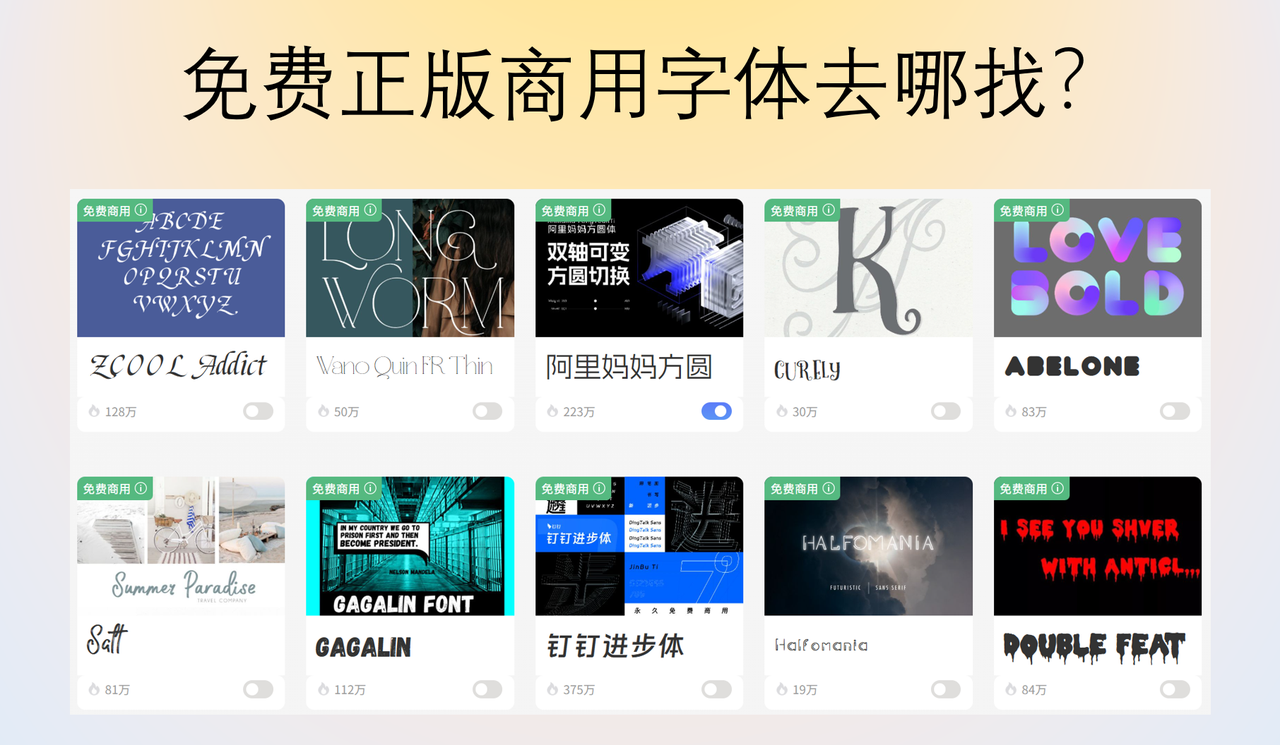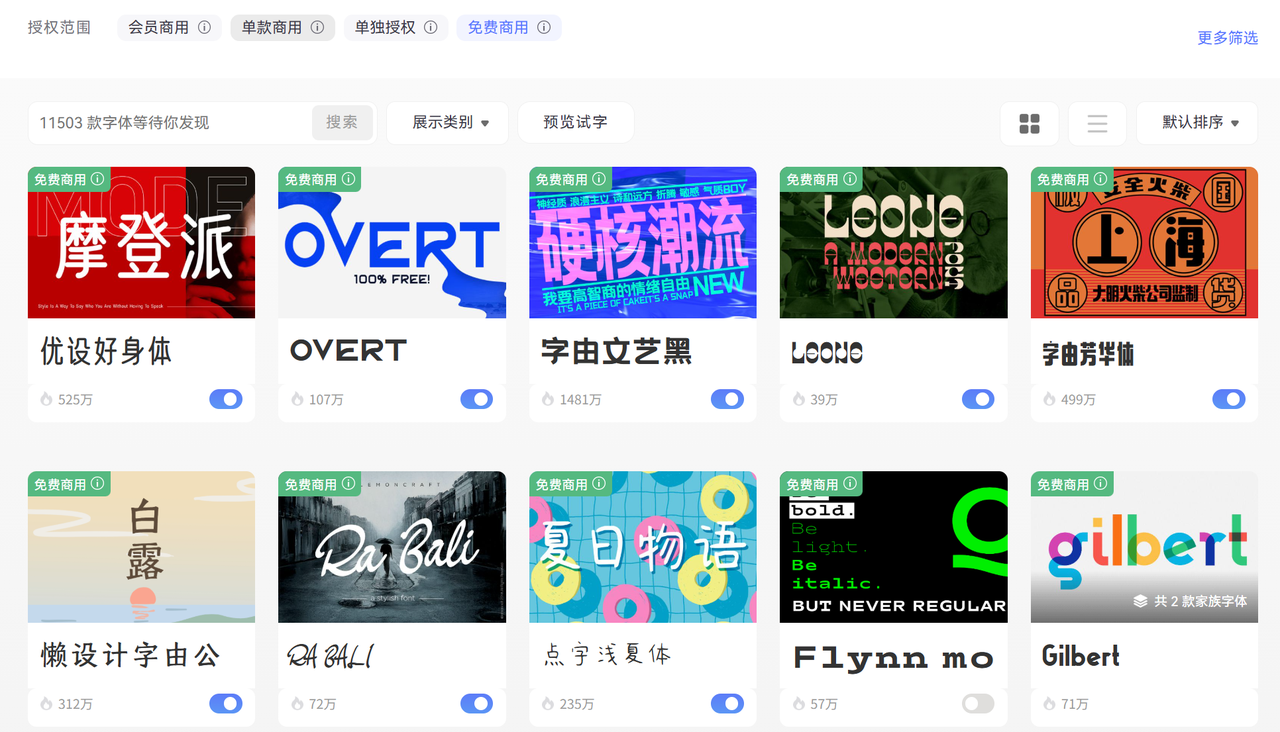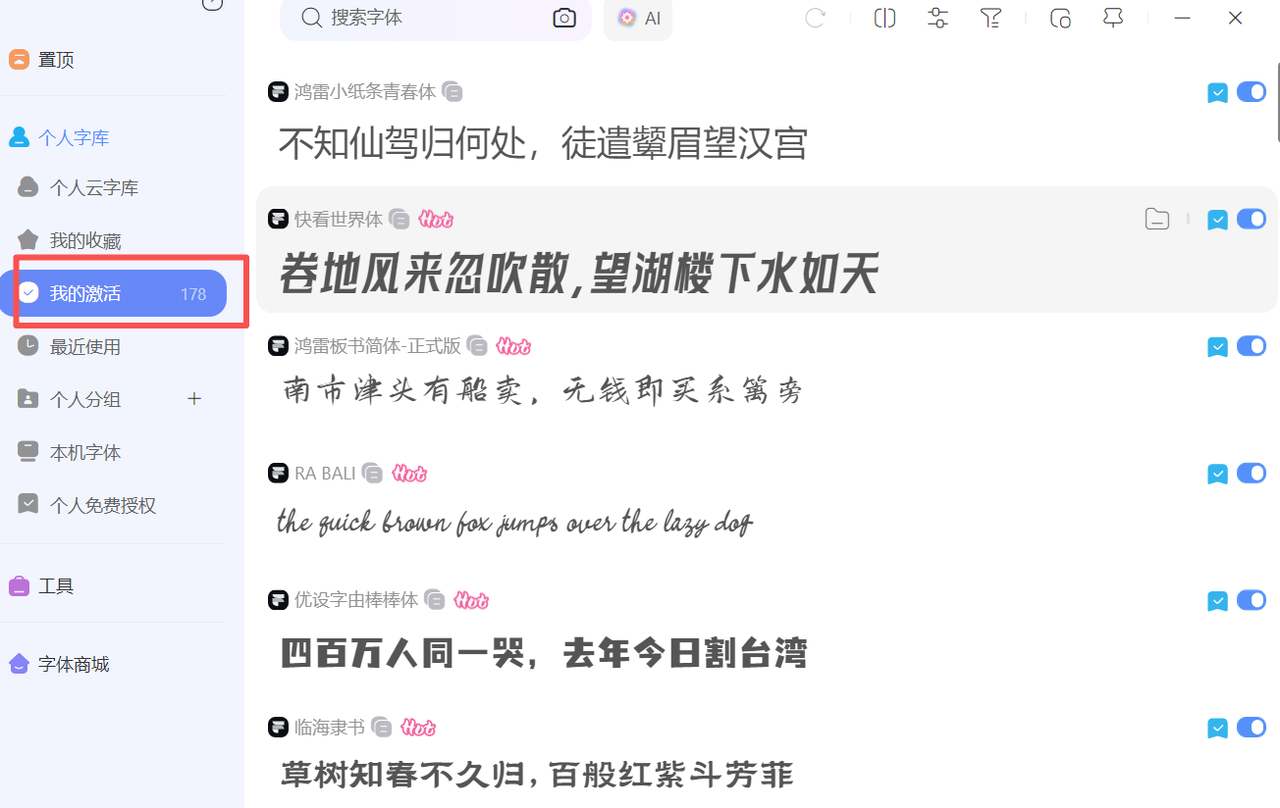
免费正版商用字体去哪找?6个靠谱平台推荐
作为设计师和内容创作者,我深知免费正版商用字体的重要性。每当开始一个新项目,最头疼的问题之一就是:去哪里找可以商用的免费字体?用错字体可能面临法律风险,而付费字体又增加成本。经过多年实践,我整理了几个可靠来源,希望能帮助你轻松解决这个难题。
在众多字体平台中,我特别推荐字由。它不仅界面友好,更重要的是提供了一批真正可以免费商用的优质字体。它的字体分类清晰,授权信息透明,完全不用担心版权问题。
字由上几款我经常使用的免费商用字体:
- 站酷快乐体:圆润可爱的风格,适合轻松活泼的设计项目
- 思源黑体:Adobe与Google合作开发,现代感强,支持多种语言
- 阿里巴巴普惠体:由阿里巴巴发布,包含多种字重,适用场景广泛
- 庞门正道标题体:气势磅礴,非常适合大标题使用
- 霞鹜文楷:优雅的中文楷体,古典而不失现代感
这些字体不仅美观,更重要的是它们的授权条款明确允许商业用途,对个人创作者和小型企业特别友好。
下载正版商用字体其他5个免费正版商用字体平台
除了字由,我还收集了几个同样优质的免费商用字体资源:
Google Fonts
- 全部字体开源免费商用
- 支持多语言,特别是西文字体丰富
- 可直接通过CSS引入网页项目
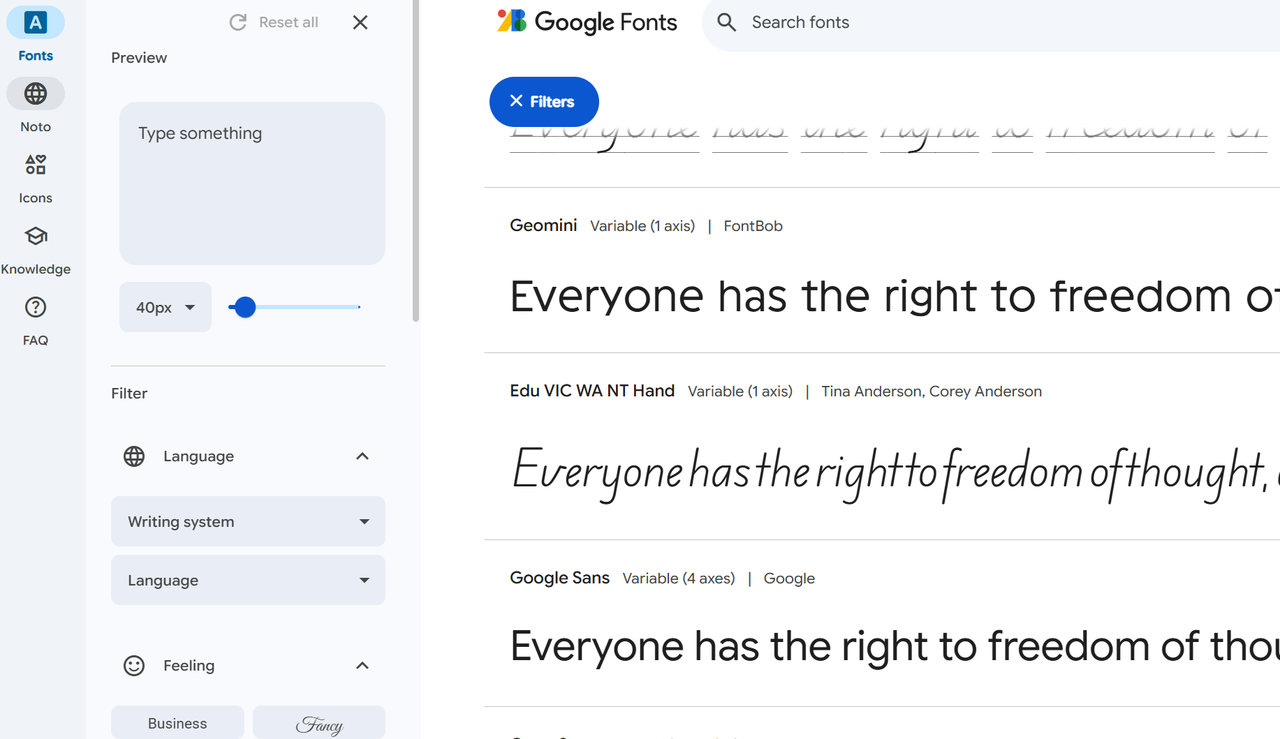
100font
- 专门收集免费商用中文字体
- 分类详细,可按风格查找
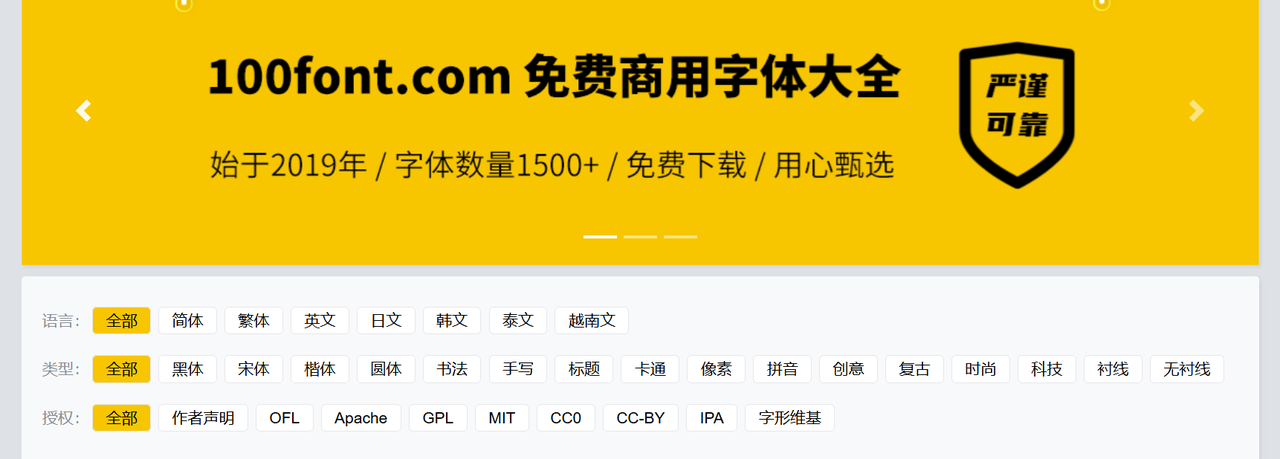
Font Squirrel
- 专注商业免费字体
- 每款字体都经过授权验证
- 适合品牌设计使用
- 推荐:Bebas Neue、League Gothic
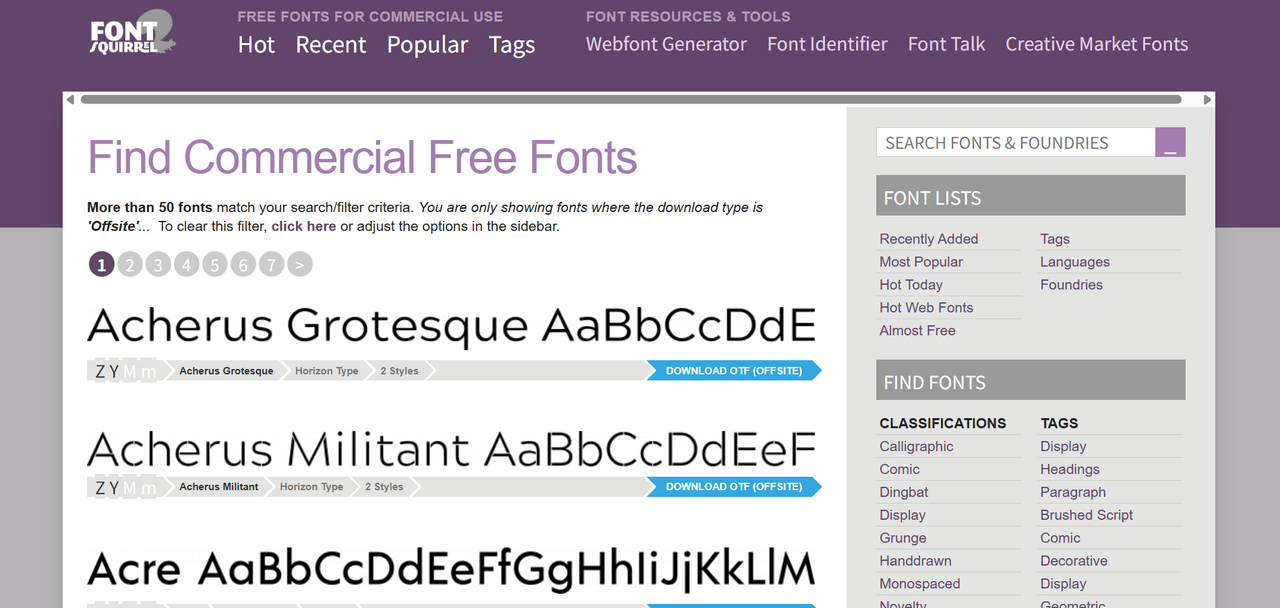
DaFont
- 字体数量庞大
- 可按"100%免费"筛选商用字体
- 创意类字体特别多
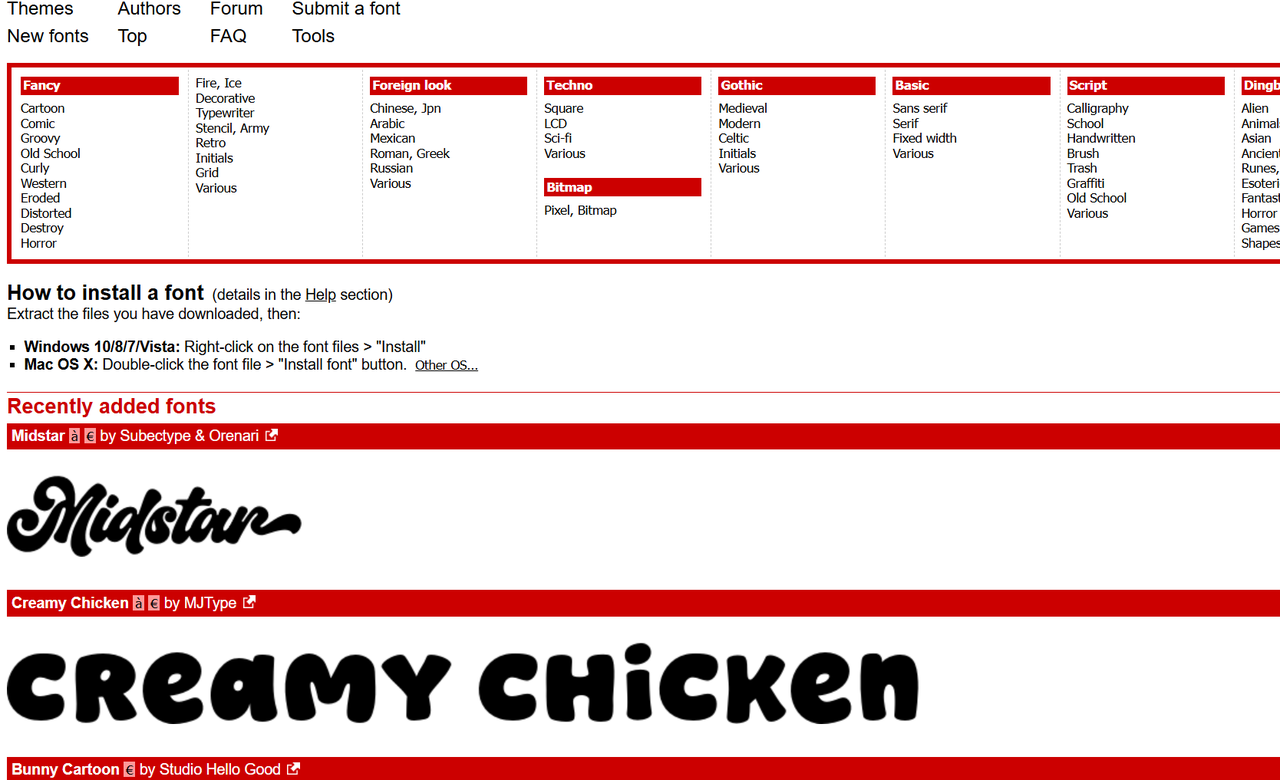
GitHub
- 很多开发者分享开源字体
- 可以找到一些独特的设计
- 需要一定的技术基础
- 推荐搜索关键词:"free commercial font"
使用免费商用字体的小技巧
在长期使用各种免费商用字体的过程中,我总结了几点经验:
- 商用项目尽量选择流行度高的字体,避免生僻字体在不同设备上显示异常。
常见问题解答
Q:中文字体和西文字体如何搭配?
A:我通常会选择同一种风格的字体,比如现代无衬线体搭配使用。思源黑体与Roboto就是很好的组合。